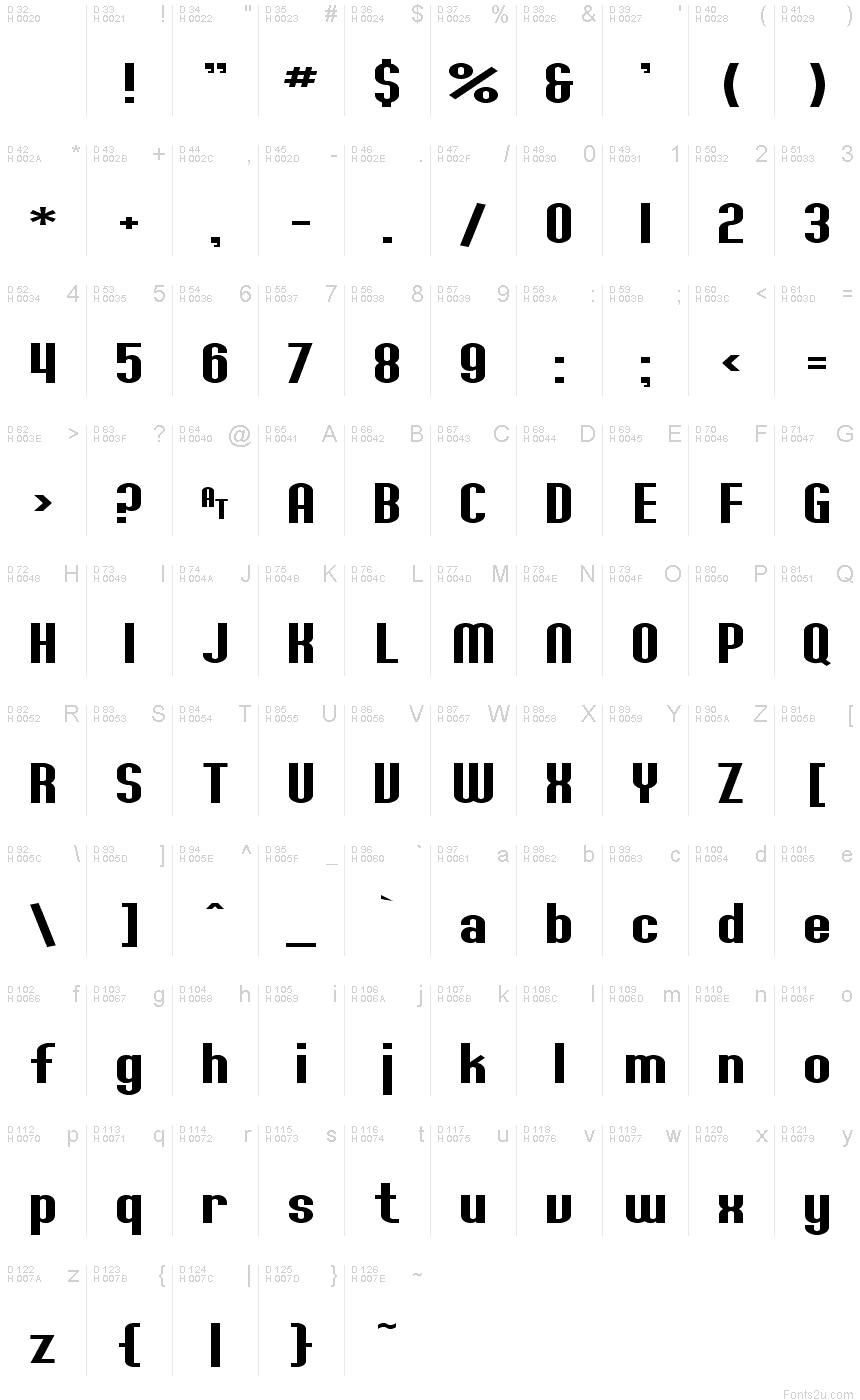
SF Willamette Extended od ShyFoundry je bezplatné geometrické bezpatkové písmo s přímočarým, plakátovým nádechem. Velká písmena působí masivně a kompaktně, s hranatými tvary, výraznými vertikálními řezy a širokým, blokovým rytmem, který dodává i jednoduchým znakům stemplovaný, architektonický charakter.
Díky tomu je přirozenou volbou pro plakáty, obaly desek, sportovní branding, titulky a výrazné nadpisy, kde pár písmen musí mít skutečnou váhu. Jako bezplatný font se hodí i pro monogramy, merchandising a krátké titulky, zejména pokud potřebujete, aby husté tvary a úzké vnitřní prostory vytvořily kompaktní a solidní nadpis.